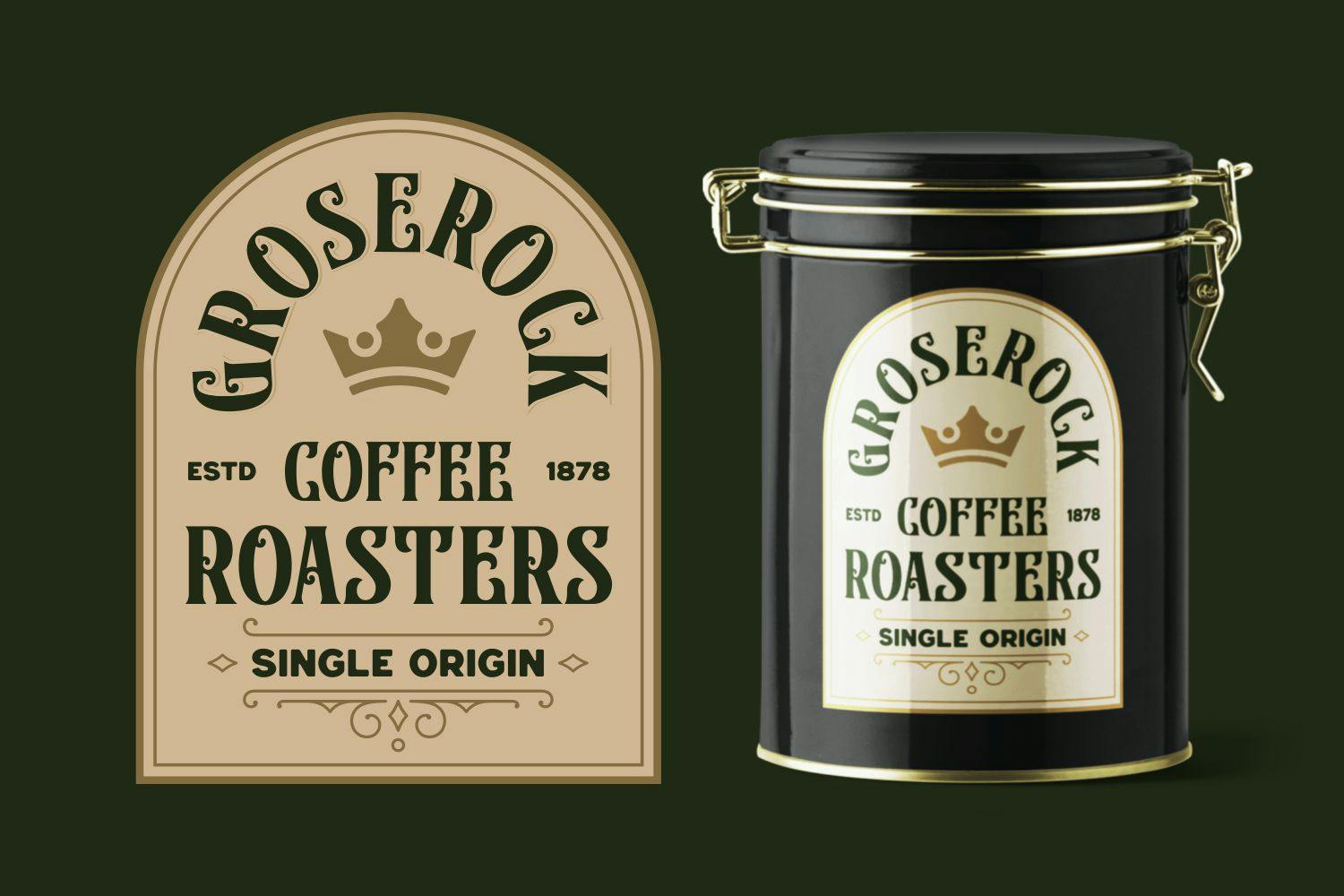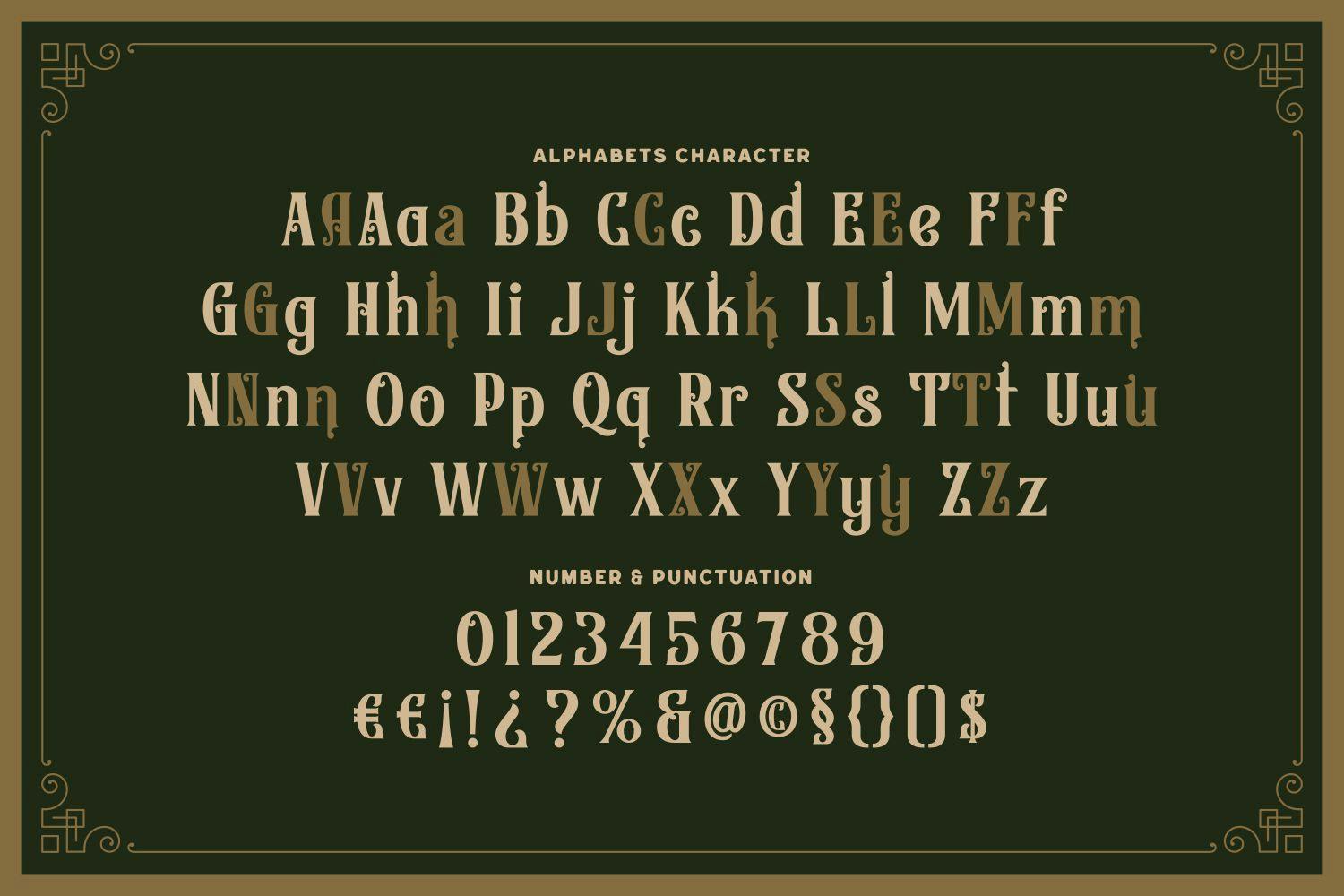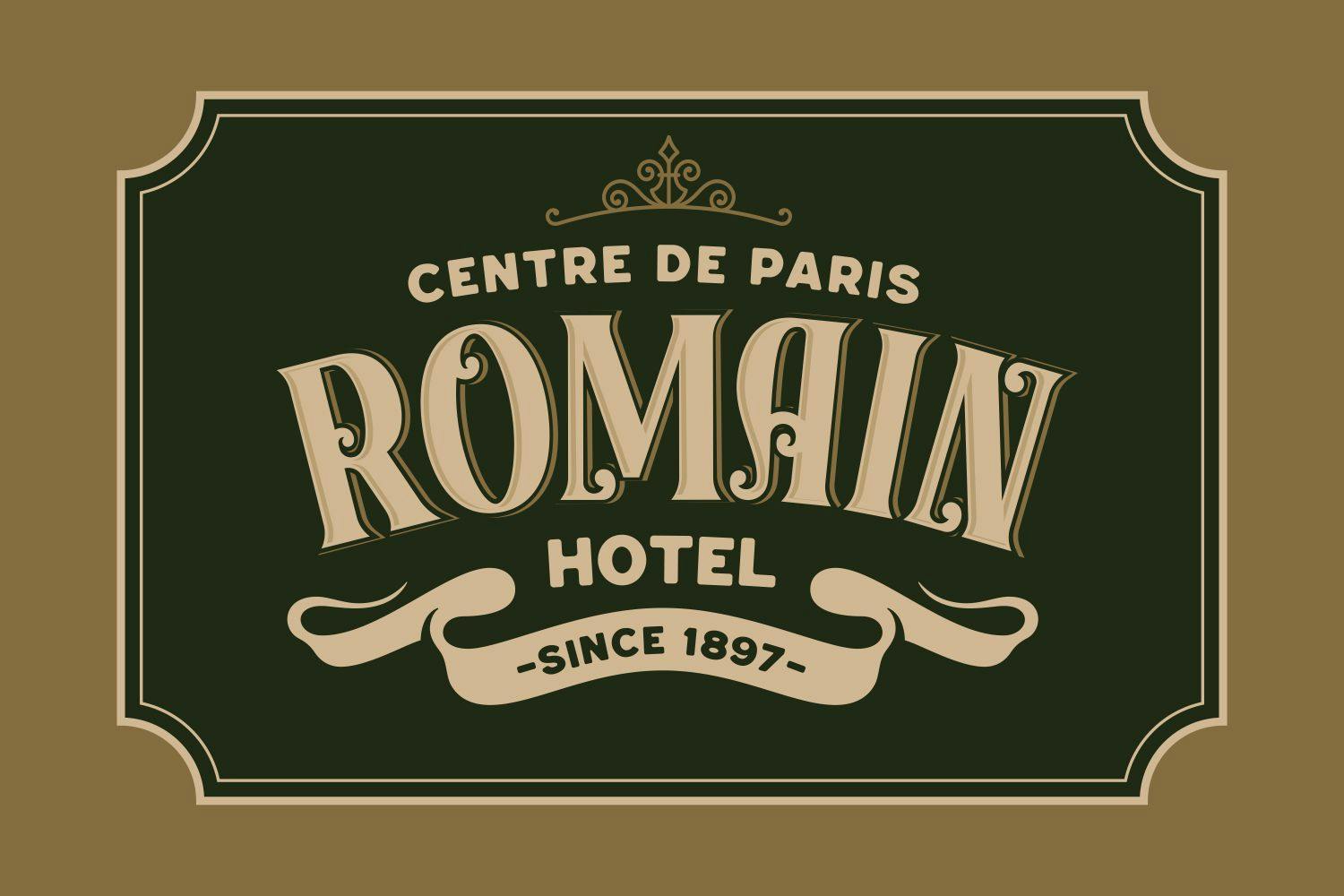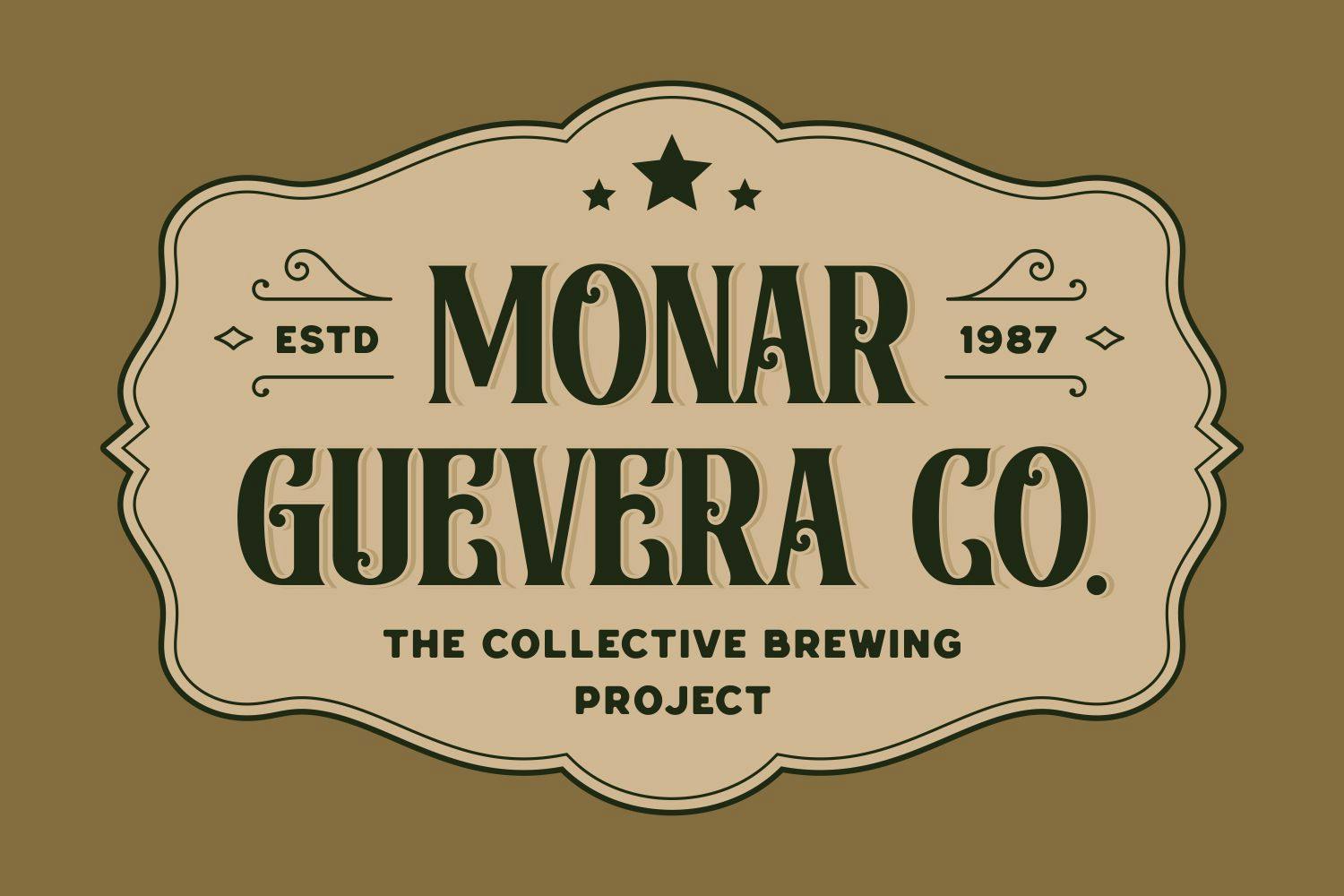
فونت Andisek یک فونت وینتیج است که الهامگرفته از هنر و خطاطی زیبای تابلوهای قدیمی میباشد. این فونت با کاراکترهای طراحی جایگزین منحصر به فرد، جلوهای زیبا و هنری به طراحیهای شما میبخشد.
فونت Andisek برای طراحی لوگو و بستهبندی، عبارات کوتاه یا سرخطها بسیار مناسب است. با استفاده از این فونت، میتوانید پروژههای خود را به سطح جدیدی از جذابیت برسانید.